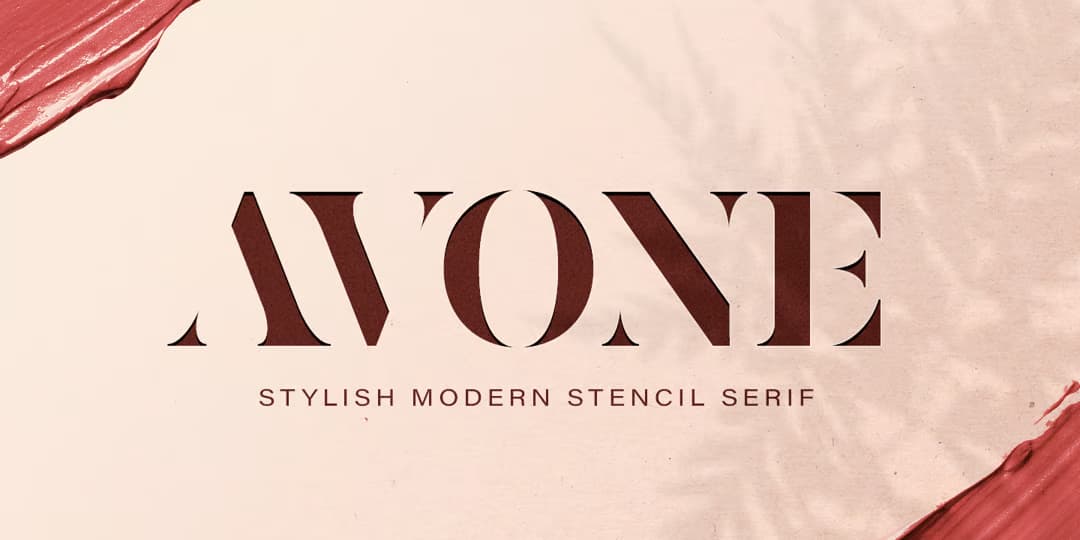
Avone
ゴージャス感のある太めのモダンローマンディスプレイ。元々かなりコントラストが強くヘアラインが細い書体だが、見ての通りヘアラインを完全にすっ飛ばしたステンシルタイプのものがあり、なぜかよりゴージャス感が増してカッコいい。とはいえそれだけで、他にはこれといった特徴はない(笑)のだが、妙に出来がいいので紹介してみた。クラシカルな高級感の演出には持って来いだろう。